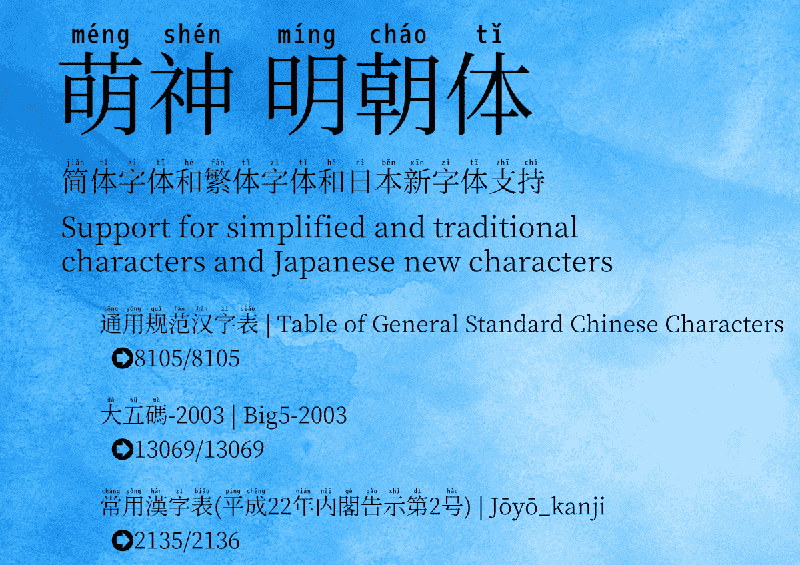
萌神拼音体是一款用于学习中国汉字的字体,由思源宋体和M+字体进行改造而成,采用SIL Open Font License 1.1授权协议发布的一款免费商用字体。 这是一种用来帮助学生更快地学习和阅读汉语的字体。在某些设计场景其实也挺实用的,特别是对教育类的设计比较有用。
萌神拼音体基本上是可以显示日语、简体字和繁体字的字体,是在简体字和繁体字中加入拼音的字体的制作。